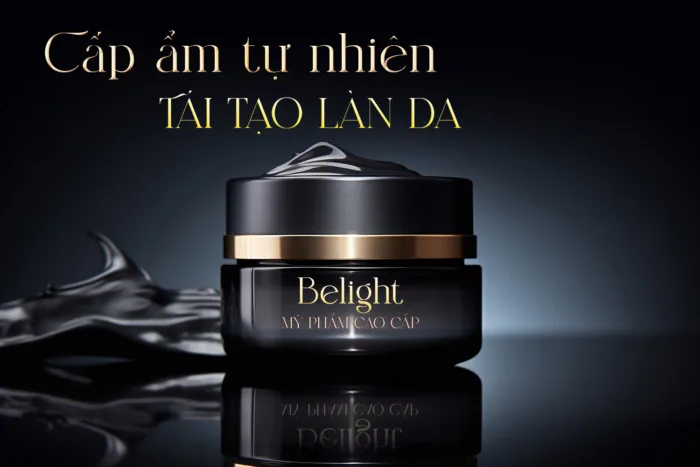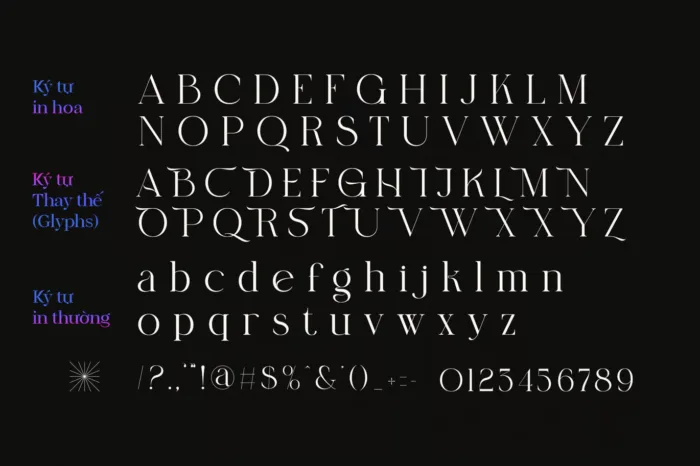
DVN Belight Việt hóa – Font chữ nét mỏng sang trọng và tinh tế
DVN Belight Việt hóa là một font chữ serif tinh tế, mang đậm phong cách sang trọng và hiện đại, được thiết kế để đáp ứng nhu cầu sáng tạo của các nhà thiết kế Việt. Với các nét chữ thanh mảnh, mềm mại và những đường cong uyển chuyển, DVN Belight toát lên vẻ đẹp cổ điển nhưng không kém phần thời thượng. Font chữ này đã được Việt hóa hỗ trợ đầy đủ bảng mã tiếng Việt, đảm bảo hiển thị chính xác và đẹp mắt các ký tự có dấu.
DVN Belight lý tưởng cho các dự án thiết kế cao cấp như logo, tiêu đề, poster, hoặc ấn phẩm thời trang và nghệ thuật. Sự kết hợp hài hòa giữa các chữ cái tạo cảm giác nhẹ nhàng, thanh thoát, gợi lên hình ảnh của ánh sáng và sự tinh tế. DVN Belight Việt hóa không chỉ là một font chữ, mà còn là nguồn cảm hứng cho những thiết kế đẳng cấp, chuyên nghiệp.